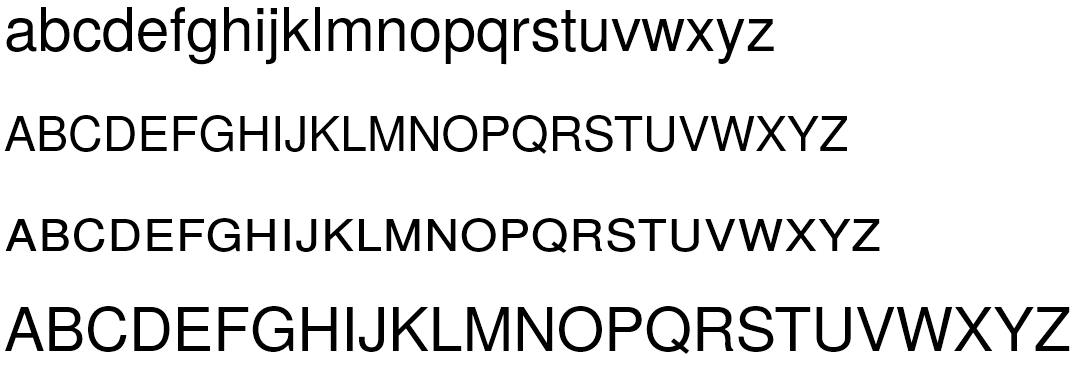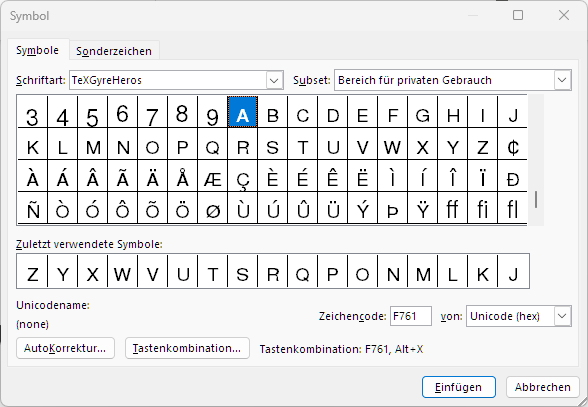
Word und Kapitälchen – TeX Gyre Heros
vielleicht weiß jemand Rat: Wenn ich in Word die TeX Gyre Heros verwende und unter Schriftart/Effekte "Kapitälchen" anhake, verwendet Word dann die ("echten") Small Caps, die zu TeX Gyre Heros dazugehören, oder bastelt es selbst welche, wie das auch passiert, wenn keine Small Caps zur Verfügung stehen? Falls Letzteres der Fall ist: Wie kriege ich Word dazu, "echte" Kapitälchen zu setzen, wenn es die gibt?
ich habe probehalber die Schrift vom Eichhörnchen runtergeladen und mir angeschaut. Alle acht Schnitte verfügen über echte Kapitälchen. Generell sollte es Word also möglich sein, SmallCaps zu setzen.
Zum Vergleich habe ich vier Zeilen abgesetzt:
1. Minuskeln,
2. Kapitälchen
(durch Zuweisen des Formats, wie du es in deinem Screenshot gezeigt hast),
3. Kapitälchen einzeln eingefügt
(Einfügen > Symbol > weitere Symbole;
Kapitälchen befinden sich fast ganz am Ende der Zeichenpalette*) und
4. Majuskeln.
Hier das Ergebnis:
TeXGyreHerosSmallCaps.png
Wie man sieht, unterscheiden sich zweite und dritte Zeile. Es scheint also so, als würde Word künstliche Kapitälchen erzeugen, wenn man die Formateinstellung über Schriftart > Effekte > Kapitälchen ansteuert.
* So sieht das bei mir aus:
Es scheint also so, als würde Word künstliche Kapitälchen erzeugen, wenn man die Formateinstellung über Schriftart > Effekte > Kapitälchen ansteuert.
So ist es.
Wie man sieht, unterscheiden sich zweite und dritte Zeile. Es scheint also so, als würde Word künstliche Kapitälchen erzeugen, wenn man die Formateinstellung über Schriftart > Effekte > Kapitälchen ansteuert.
erstmal vielen Dank für deine Mühe! Dass Word künstliche Kapitälchen erzeugt, habe ich vermutet. Verstehe ich deinen Screenshot richtig, dass ich echte Kapitälchen immerhin verwenden kann, wenn ich sie manuell als Sonderzeichen ansteuere?
Ja, du kannst sie mühsam als Einzelglyphe einfügen, aber nicht über eine Formatvorlage ansteuern. Das Einfügen funktioniert so:
1. Reiter ›Einfügen‹ auswählen
2. Button ›Symbol‹ anklicken
3. Schaltfläche ›Weitere Symbole …‹ anklicken
4. Zeichen aus der Glyphentabelle anwählen*
5. Schaltfläche ›Einfügen‹ anklicken
* Bei der von mir verwendeten TeX-Gyre-Heros Regular befanden sich die Kapitälchen fast am Ende der Zeichentabelle.
Ein Doppelklick auf das Zeichen geht auch.
Ich mach es meistens so, dass ich erst alle für die Namen nötigen Kapitälchen mit der Zeichentabelle erzeuge und dann den Rest dazwischentippe.
dass ich erst alle für die Namen nötigen Kapitälchen mit der Zeichentabelle erzeuge und dann den Rest dazwischentippe
Was tippst du zwischen die Kapitälchen? Ich steh gerade wohl echt auf dem Schlauch.
Ich hole mir aus der Zeichentabelle „ülleraierchmidtimmermann“ und tippe dann „Die Konsequenzen die M aus den Ergebnissen von M und S zog, ließen Z nicht kalt“ dazwischen, so dass sich „Die Konsequenzen die Müller aus den Ergebnissen von Maier und Schmidt zog, ließen Zimmermann nicht kalt“ ergibt.
Ja, du kannst sie mühsam als Einzelglyphe einfügen, aber nicht über eine Formatvorlage ansteuern. Das Einfügen funktioniert so:
Perfekt. So groß ist der Aufwand zum Glück nicht; es geht – wie in dem Beispiel von HennigH – nur darum, gelegentlich Eigennamen hervorzuheben.